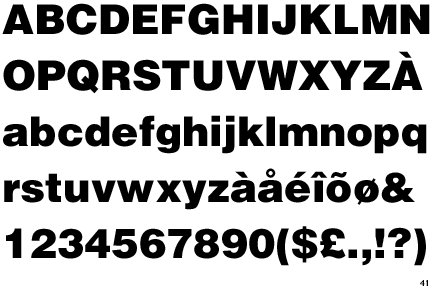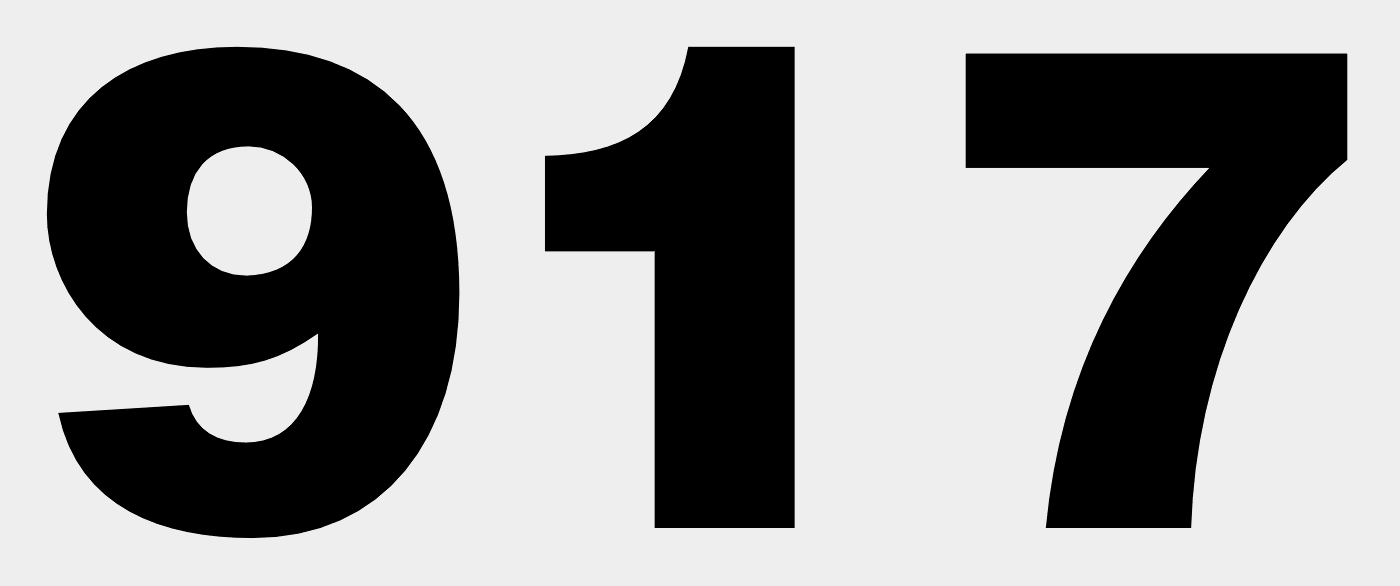
Hat jemand eine Ahnung was das für ne Schriftart sein könnte?
hat von euch vielleicht jemand eine Ahnung was das für ne Schriftart sein könnte?
Comic Fonts? Da gibt es doch was von Blambot?
Die 917 sind sehr wahrscheinlich eine verrasterte und weichgelutschte Helvetica Black.
Helvetica Black
Designer: Max Miedinger
Year: 1956-58, 1985
Sagt mal, die 917 ist doch hundertprozentig keine Helvetica Black …  :neenee:
Ich hab mal eine "Helvetica Black Condensed" verzerrt und drübergelegt, das könnte eher passen.
Ja, stimmt möglicherweise. Da ich keine Helvetica Black Condensed auf der Kiste habe konnte ich das nicht so schnell und ohne Aufwand ausprobieren. Es ist wahrscheinlich die Condensed weitgezogen. Na ja, als geschändete Leich sehen sich die Lettern alle gleich ... oder so. Damit ist der Fall endgültig abgeschlossen.